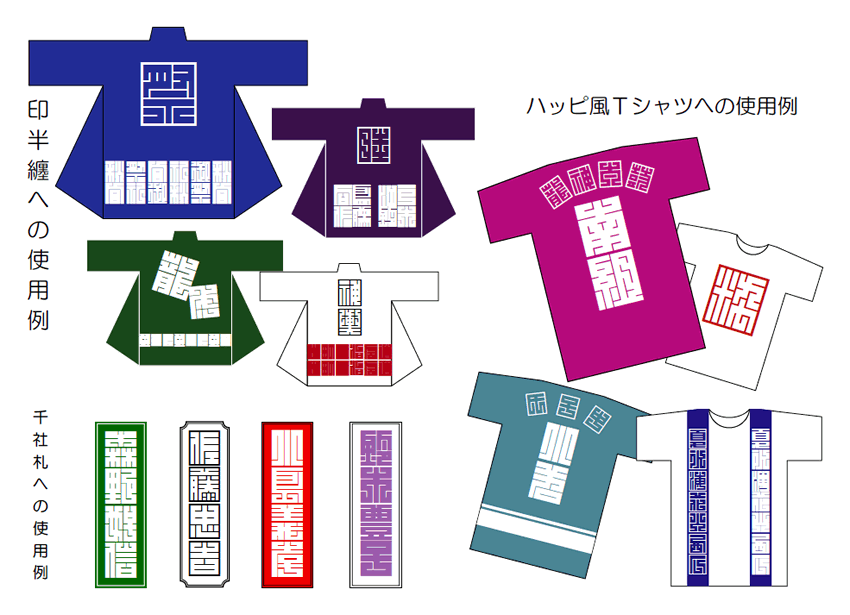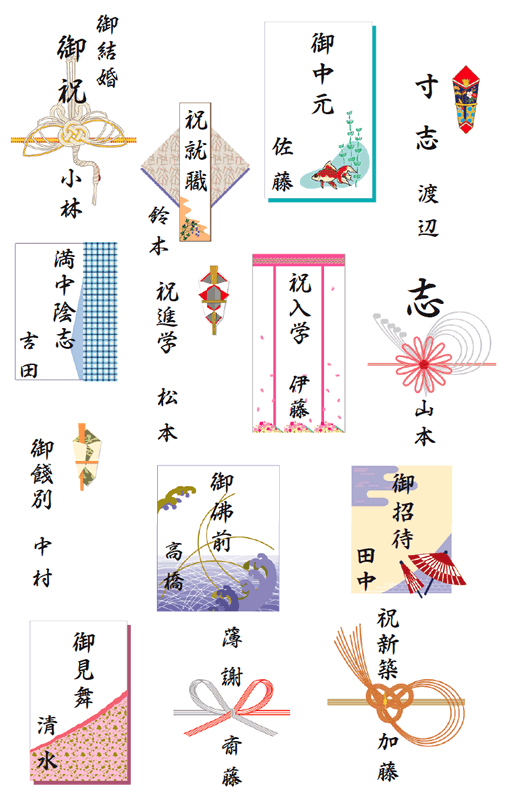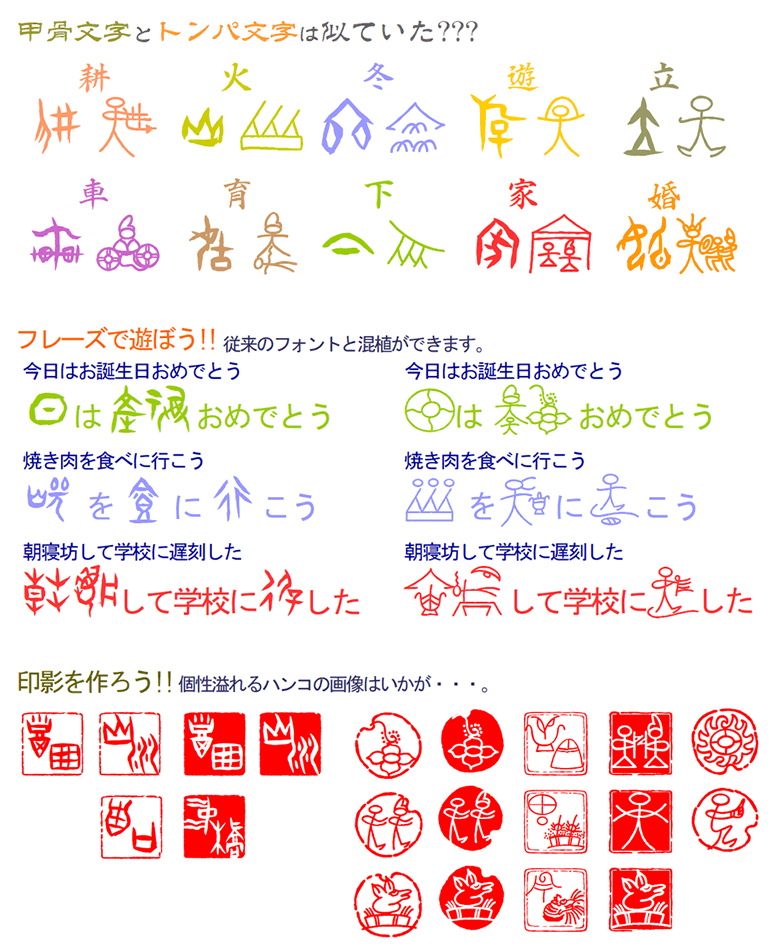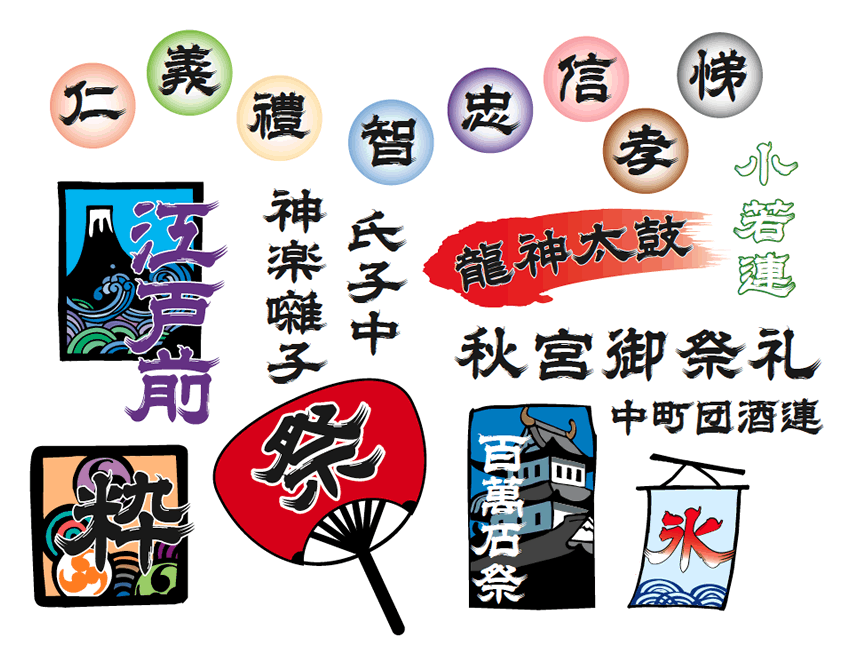
本套白舟四季词字体,是适合表现日本四季的和风情趣的字体。每一套字体都是针对不同的季节风格而设计。春天是入学、升学、就业的季节。可以用书代、封面、姓氏等。说到夏天,就是祭典,准备了非常有气势的祭典式字体。艺术之秋请尽情享受古代文字的探索和继承的文字的历史。冬天是岁末,请用白舟书体装饰适合迎接新年的贺年片。
白舟楷書御祝、白舟行書御祝支持的汉字
白舟角崩白文、白舟角崩朱文、白舟髭隷支持的汉字
白舟甲骨、遊トンパ支持的汉字
白舟楷書年賀、白舟行書年賀、白舟草書年賀、白舟隷書年賀、白舟古印体年賀、白舟篆書年賀、白舟小篆年賀支持的汉字